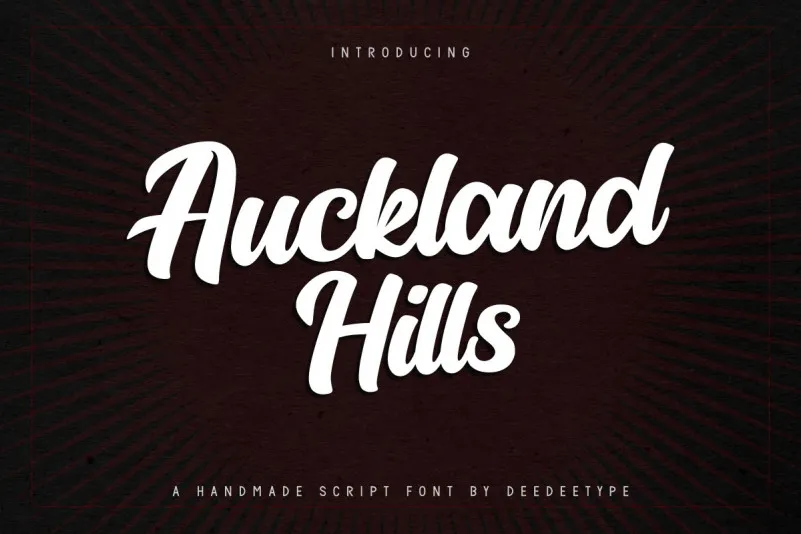
Auckland Hills Font – Download Grátis
Auckland Hills Font é uma fonte script moderna e sofisticada que pode complementar sua paleta visual com estilo elegante e versátil. Confortável para uso em diversas aplicações como identidades corporativas, convites de casamento, cartões de agradecimento ou mesmo selos e logotipos. Com um ar forte e confiante, esta fonte adorna seus projetos com personalidade nostálgica e dinâmica, garantindo que seu design seja único e memorável. Perfeita para aqueles buscando uma opção versátil entre o elegante e o atemporal. Experimente esta fonte em sua próxima peça de arte digital e veja como ela pode dar um toque especial à sua criação.